Neues zur Obi-Schrift
Christian Werler, Factor Design Zürich, liefert
hilfreiche Informationen zur Obi-Schrift. Das
Copyright liegt bei Elsner & Flake (was den
Font-Metadaten zu entnehmen ist), es gibt insgesamt 5
Schnitte (Regular, Bold, Black, Condensed, Bold
Condensed) und spezielle Anweisungen für das Setzen
von Ziffern auf Preisschildern. Ein paar Screenshots:
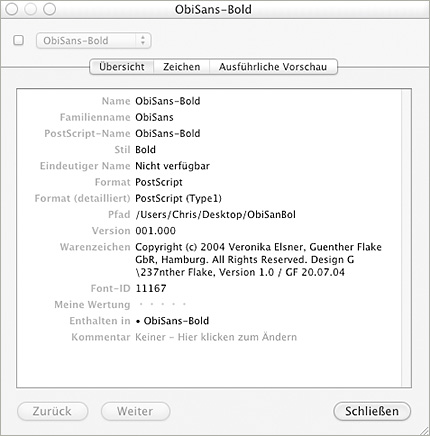
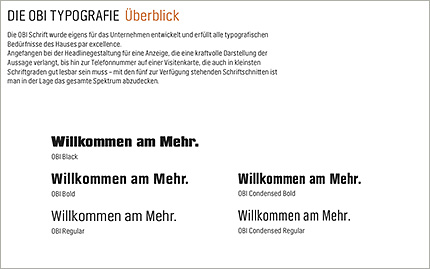
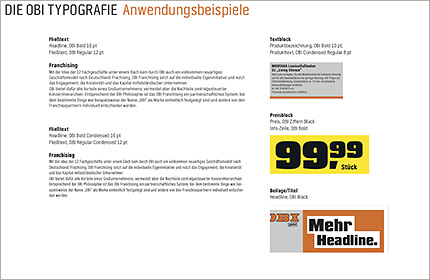
Wanted: Wer kennt die Obi-Schrift?
Robert M. Schöne fragt sich: »Welche
Schrift verwendet Obi? ... Ich war vor kurzem wieder
dort, ... während sich meine Freundin noch um den
Pflanzeneinkauf kümmerte, schaute ich mir die neue
Hausschrift genauer an. Sie kam richtig gut rüber auf
den orangefarbenen Plakaten. Sie hat verschiedene
Strichstärken und wirkt ziemlich robust. Ich finde:
sie passt wunderbar zu einem Baumarkt, eine Mischung
aus »Aachen« und »Compacta«, aber moderner umgesetzt.
Mir ließ der Font keine Ruhe. Zuhause angekommen habe ich Google gequält, aber ohne Erfolg. Kein Hinweis auf Designer oder Fontnamen.«
Wer weiß mehr?
WM-Trittbrettfahrer: letzte Folge
Ich gebe auf, wegen
Trittbrettfahrer-Overkill. Die
letzten 50 Tage vor der Fußball WM laufen, und
täglich schießen neue Fußball-Produkte wie Pilze aus
Christian Werler von Factor Design Zürich schreibt mir eben: »Das 3D-Bevel-Emboss-Schlafschattenmonster hat wieder zugeschlagen. Leider sind auch die Sprechblasen in den Os entfernt worden – fand ich weniger austauschbar.« Auf der deutschen Vodafone-Seite ist die Überarbeitung bereits im Einsatz, im Mutterland findet man noch das Auslaufmodell. Permalink